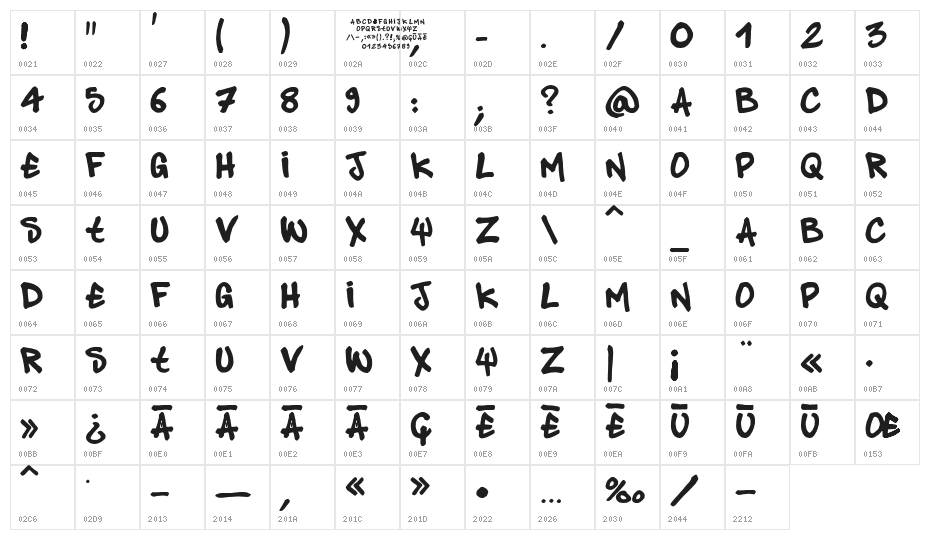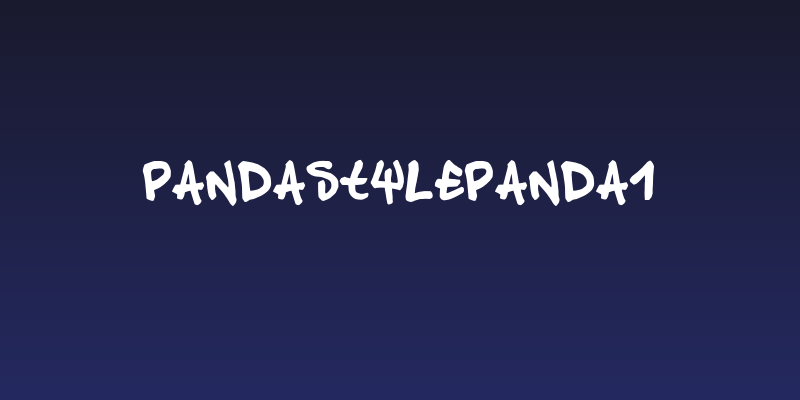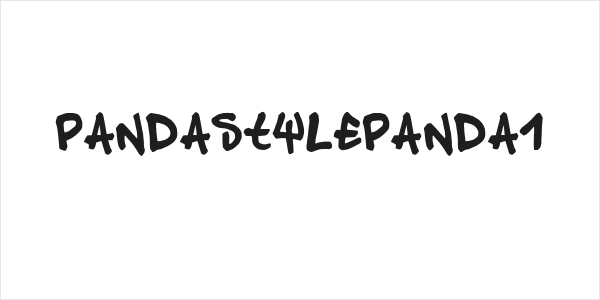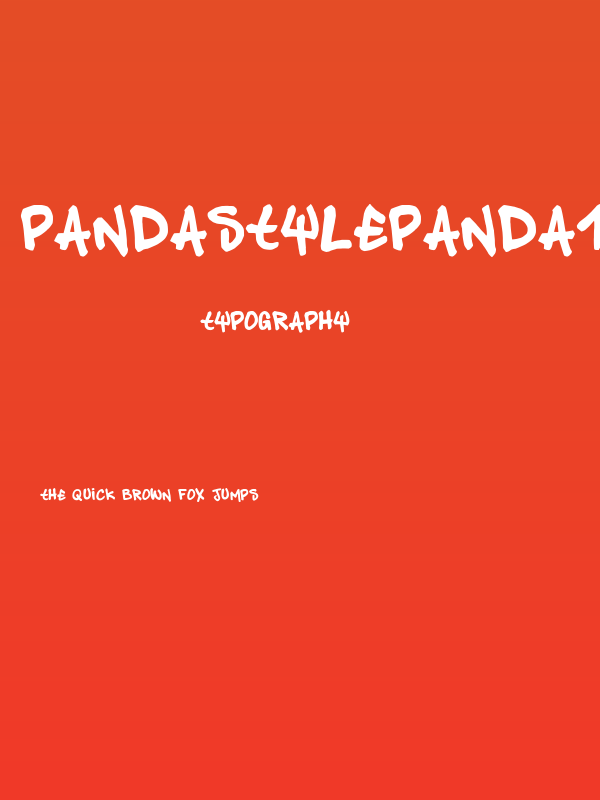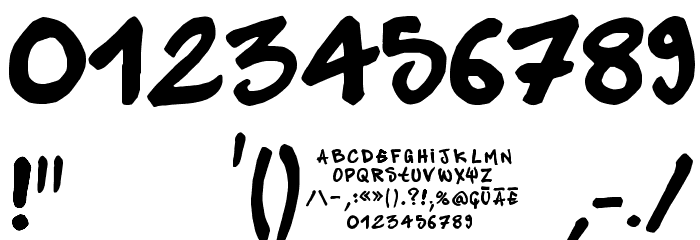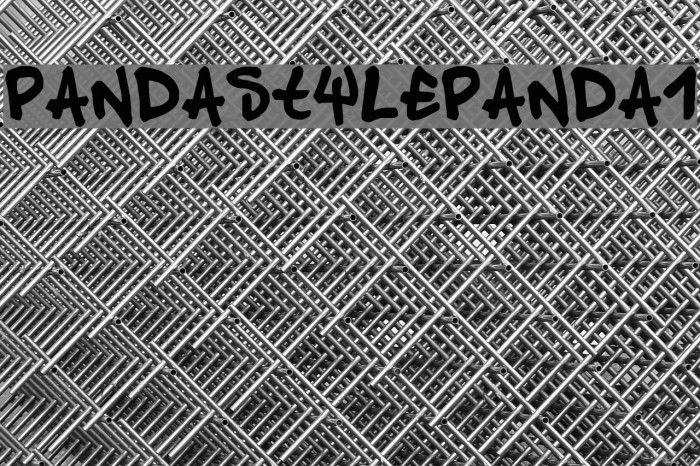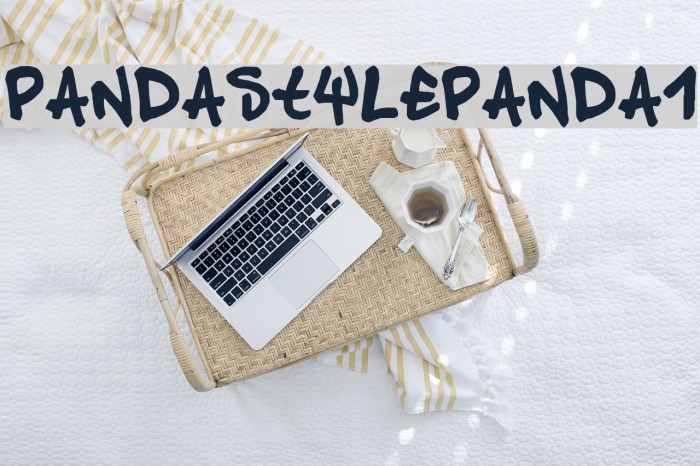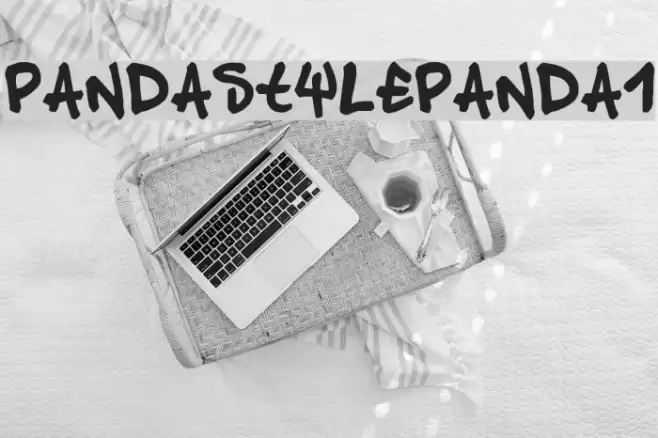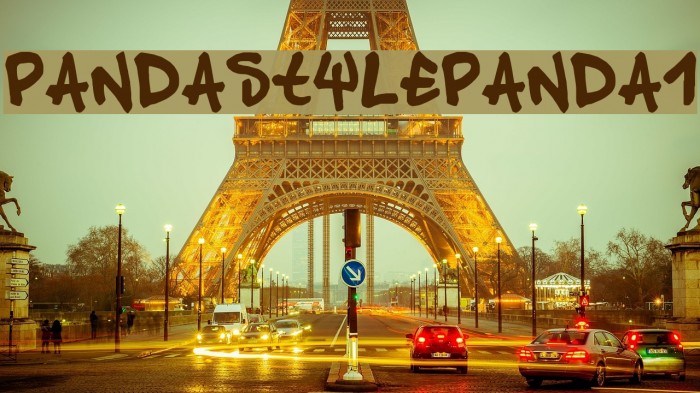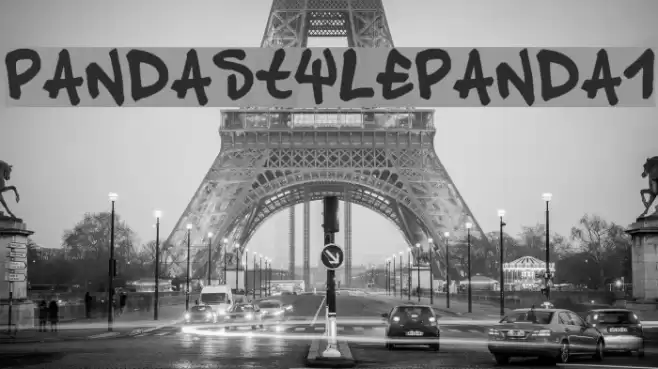
pandastylepanda1 Font
| Estilo general | Playful |
| Proyectos propuestos | Ideal for children's books, playful branding, casual invitations, and creative posters. |